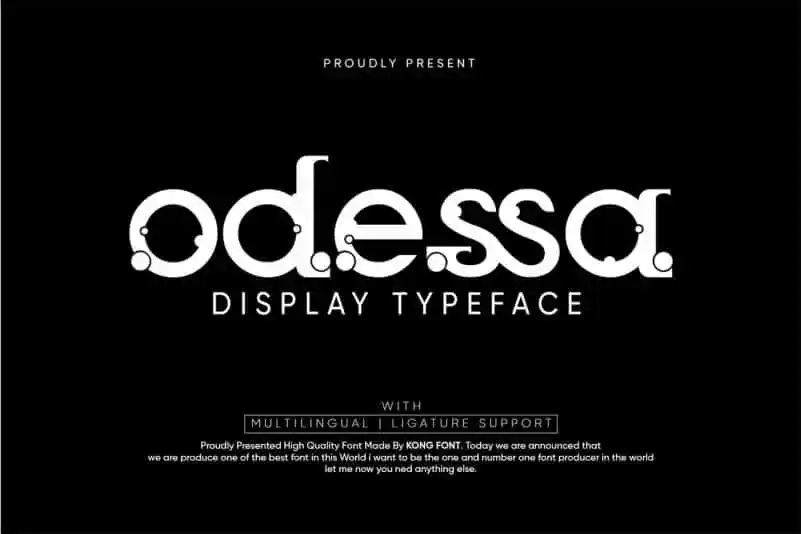
Odessa Display Font – Fonte Grátis
Odessa Display Font
A Odessa Display Font é uma tipografia sans-serif moderna baseada na tipografia utilizada nos manuais de letras do asfalto antes dos anos 1980. Esta fonte combina elementos clássicos com ajustes para se adaptar às demandas atuais, oferecendo um toque delicado que parece ter sido elaborado a mão por um estilista gráfico. Suave e elegante ao mesmo tempo, ela é perfeita para headlines, marcações e logotipos, trazendo uma sensação de simplicidade a qualquer projeto visual. Ideal tanto para projetos corporativos quanto individuais, esta fonte apresenta um estilo minimalista que contribui para uma comunicação assertiva e impactante. Não importa o tipo de trabalho, a Odessa Display Font está aqui para oferecer a perfeição gráfica necessária para qualquer projeto.